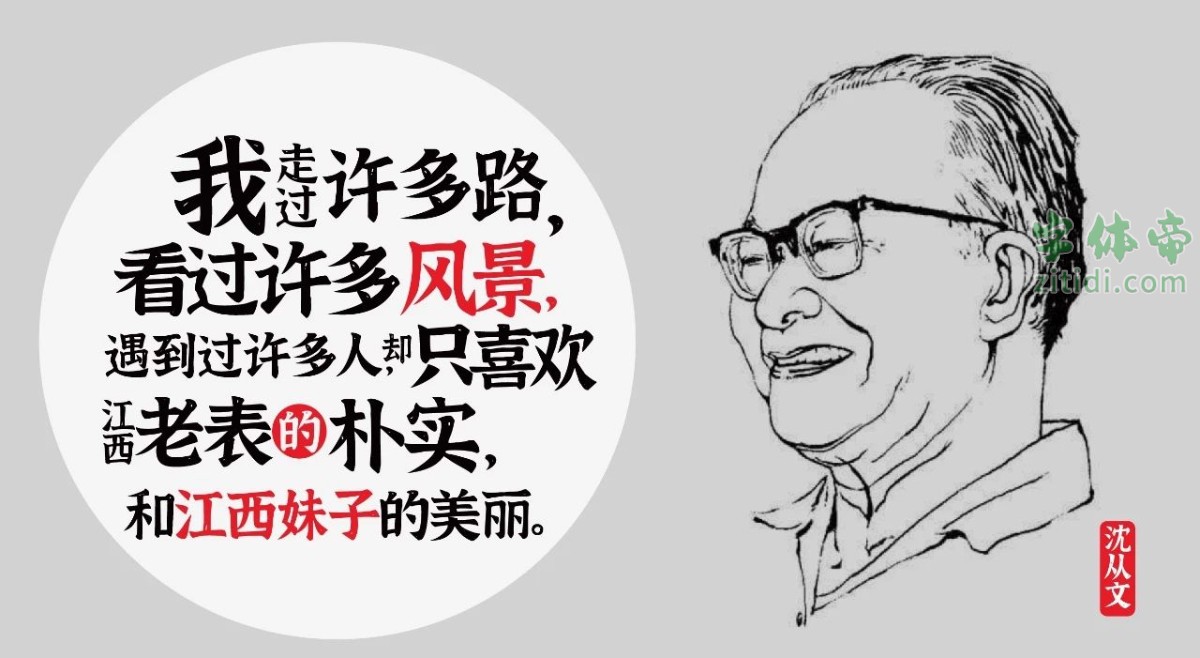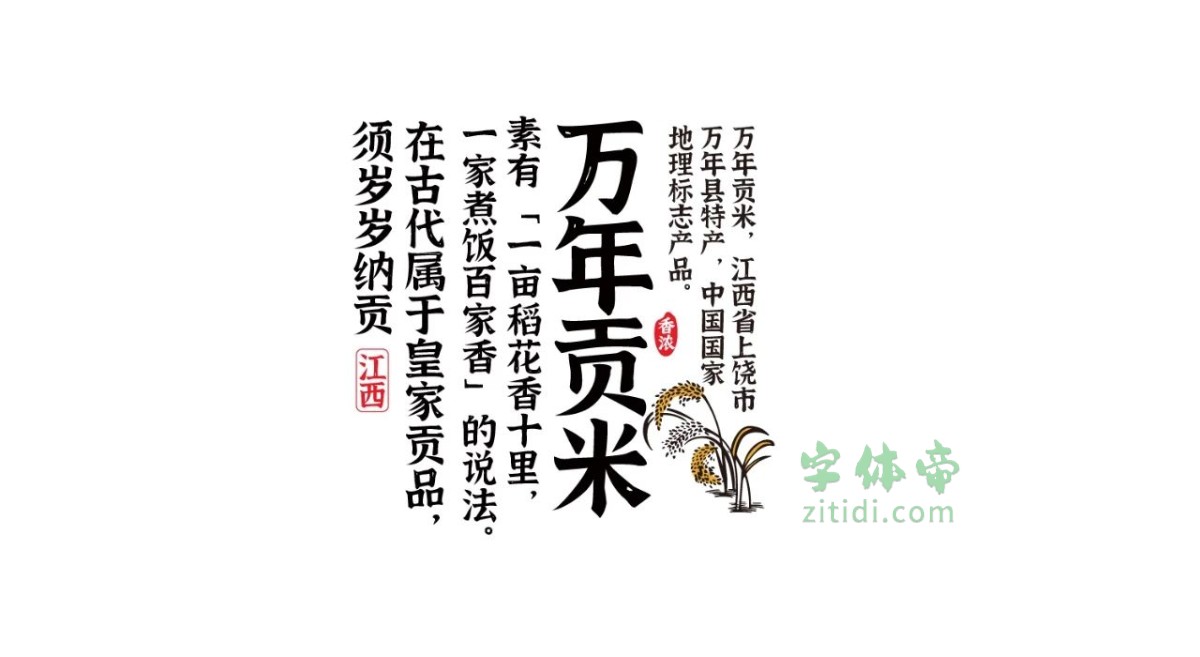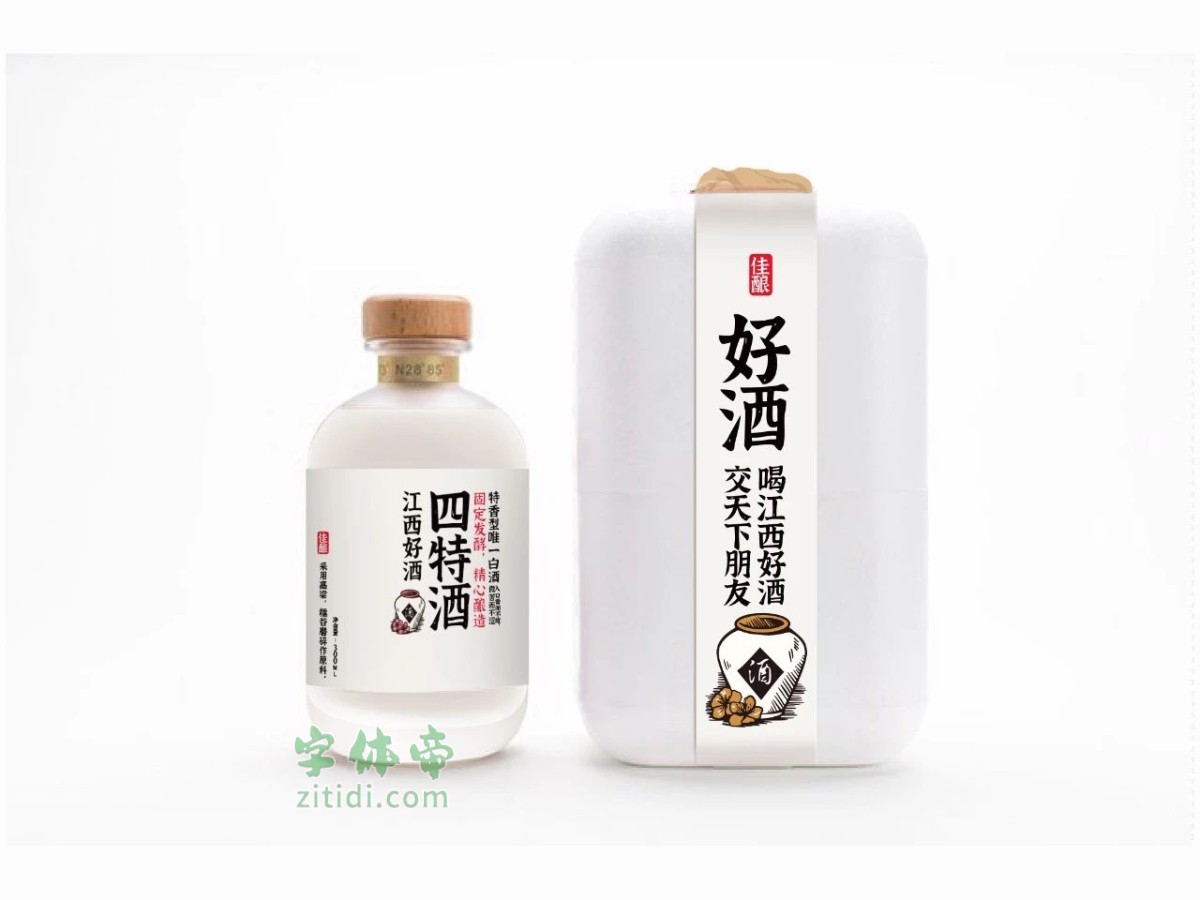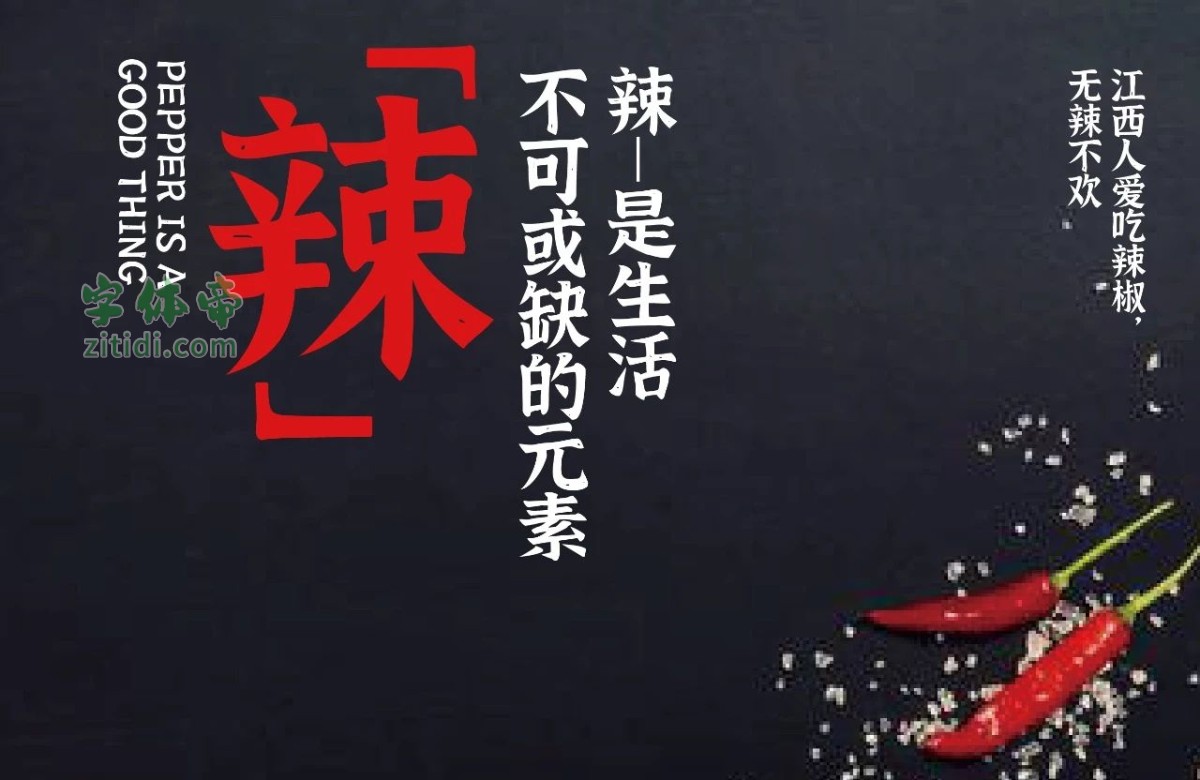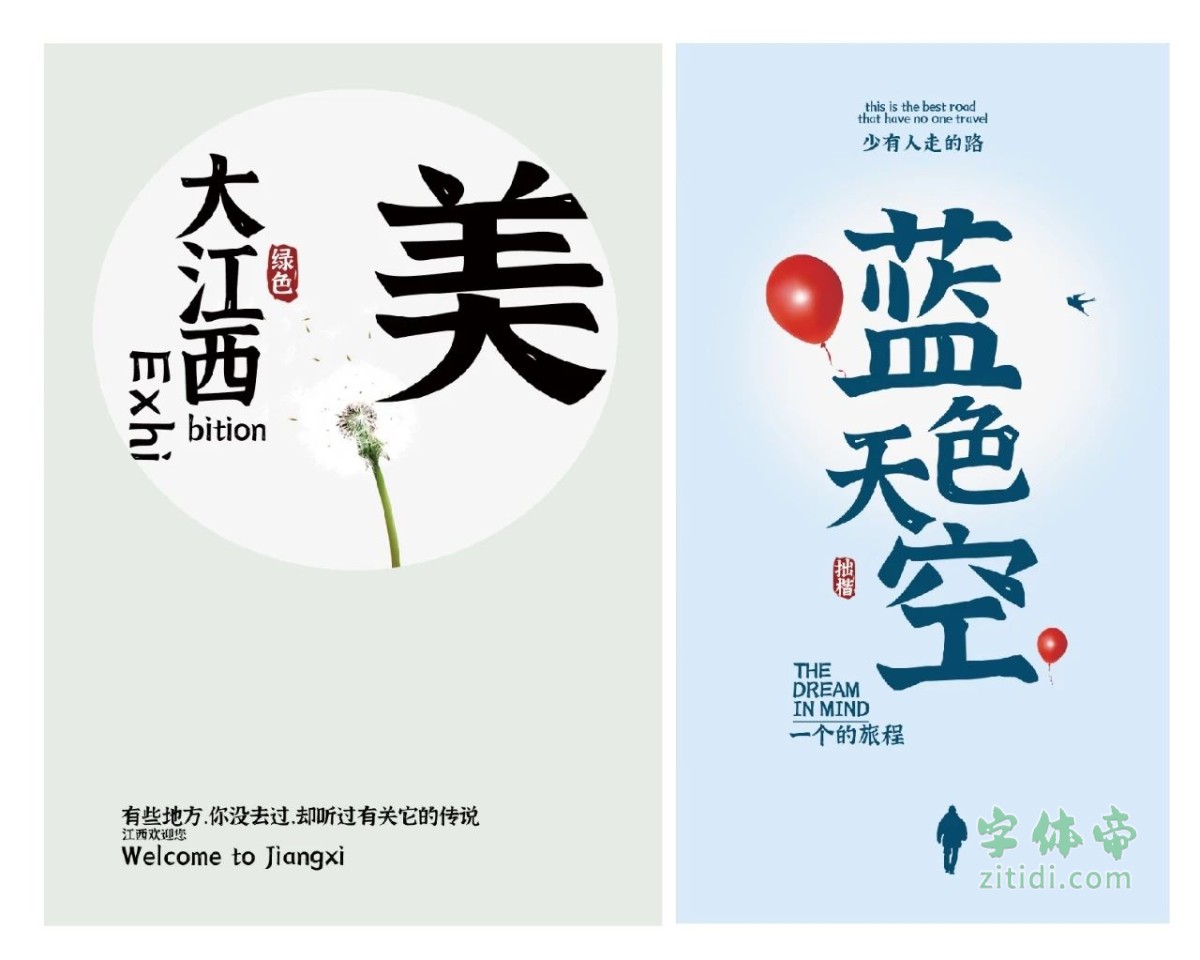
2020年元旦,我们迎来崭新的一年。在这个特别的时候,我国设计师黄煜臣也发布了今年第一套可以免费商用的字体「江西拙楷体」。做一套字体所需要花费的精力和时间是十分巨大的,黄煜臣同学半年多来夜以继日地辛劳创作才使这套非常漂亮的字体面世。大家可以加一下黄煜臣同学的微信公众号“字体树”请他喝杯咖啡或者冰阔乐吧。
这是一套手写楷体,相比电脑中标准化制作的楷体,这套字体的笔画会带有一些书写的痕迹,每个字的笔画是没有统一标准的,所以看上去显得不够规范,但是会有一种手写的自然之感。
黄煜臣如是说:
大家好,我是黄煜臣,我个人第一套字体,今天正式跟大家见面了。第一套字体的发布我内心有点小激动还有些忐忑,自己花了那么大精力去做这件事,今天终于有了一个阶段性成果,我不知道发布后会有什么效果,大家是喜欢还是无感?会不会带着期待而来,失望而去?不过俗话说的好,丑媳妇终得见公婆,藏着掖着不敢露脸只会让自己更加被动,敢于正视不同眼光的评判才是勇敢者的做法,如果有人喜欢这个丑媳妇,那将是一个意外的惊喜。
这是一套手写楷体,相比电脑中标准化制作的楷体,这套字体的笔画会带有一些书写的痕迹,每个字的笔画是没有统一标准的,所以看上去显得不够规范,但是会有一种手写的自然之感。这套字体从写手稿开始到现在的最终成品,前前后后花了近半年时间,仅仅是调节点,就花了20多天,其中的滋味做过才知道。
对于这款字体的发布,我不希望仅仅就是一款字体的展示,我希望它能发挥更大的作用,带来一些其他的价值,为了达到这个目的我想了很久——最终决定用这款字体为我们大江西做宣传。江西在各省市一直是一种低调的存在,不管是经济发展还是对外传播都是比较滞后的,我作为江西人,现在还没有能力用真金白银去为家乡做贡献,但是我可以用我的一点专业技能来为江西打打广告,做做宣传,希望让更多人认识他,喜欢他。
上面就是我这次发布的新字体,这款字的性格和江西很像, 低调内敛,朴实无华毫不张扬,就命名为江西拙楷,希望通过这套字体让江西增加点曝光度,让更多人来了解江西。
“江西拙楷2.0”是一款书写很新颖的字体,字体大方,适合各种设计作品使用!欢迎下载!